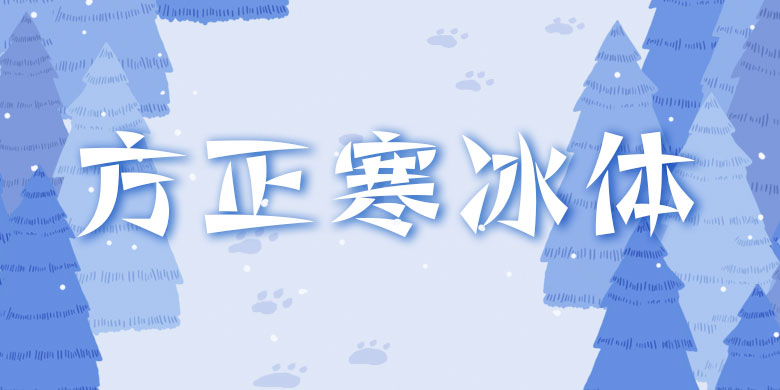
方正寒冰简体
方正寒冰简体介绍
寒冰体来源于寒冷冬日的冰棱,起笔粗重,收笔尖锐,粗细对比强烈,线条呈弧形抛物线,整体造型优美和谐、轻松谐趣、充满动感。
方正寒冰简体字体FZHanBTJW字库是一款让人赏心悦目、百看不厌的中文字体,适合各类广告和产品包装设计应用,字体大小2.83MB,格式为TTF字体,上传用户是17199970014,作者/版权方为方正字库